게시 됨: 2023-06-29스텐실 글꼴 사용을 고려했지만 어디서부터 시작해야 할지 모르십니까? 프로젝트에 독특하고 눈길을 끄는 모양을 제공할 36개의 최고의 스텐실 글꼴 목록을 편집했기 때문에 운이 좋을 것입니다.
이 기사에서는 스텐실 글꼴의 세계와 왜 디자이너들 사이에서 인기 있는 글꼴인지 살펴보겠습니다. 또한 시간 경과에 따른 역사와 진화를 포함하여 스텐실 글꼴에 대한 몇 가지 흥미로운 통계와 사실을 제공합니다.
그러나 본격적으로 들어가기 전에 스텐실 글꼴이 무엇인지 간단히 정의해 보겠습니다. 기본적으로 스텐실 글꼴은 문자가 끊어진 서체이므로 잘린 모양을 제공합니다.
스텐실 글꼴은 군사 및 산업 분야에서 일반적으로 사용되지만 광고, 거리 예술 및 기타 창의적인 분야에서도 인기를 얻고 있습니다.
스텐실 만능
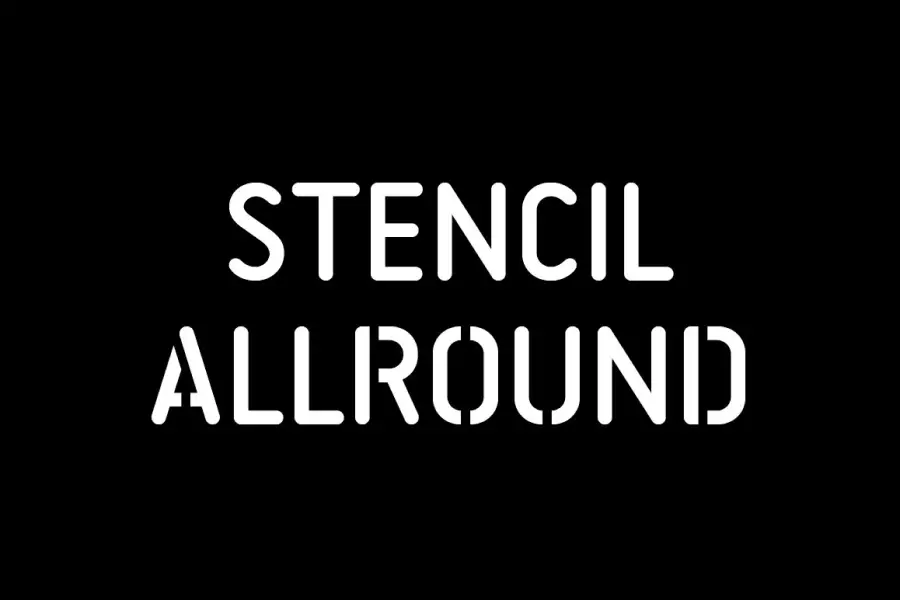
Stencil Allround는 둥근 대문자로 구성된 디스플레이 글꼴입니다. 이름에서 알 수 있듯이 스텐실 디자인이 특징이며 독특하고 눈길을 끄는 모양을 제공합니다. 포스터, 제목, 로고 등 다양한 디스플레이 프로젝트에 사용하기 위해 제작된 글꼴입니다.
Stencil Allround의 주요 기능 중 하나는 모서리가 둥글어서 부드럽고 접근하기 쉬운 모양을 제공합니다. 폰트도 가독성이 높아 본문이 큰 텍스트에 사용하기에 적합합니다. 또한 스텐실 디자인은 전통적인 글꼴과 차별화되는 추가 레이어를 제공합니다.
콰스
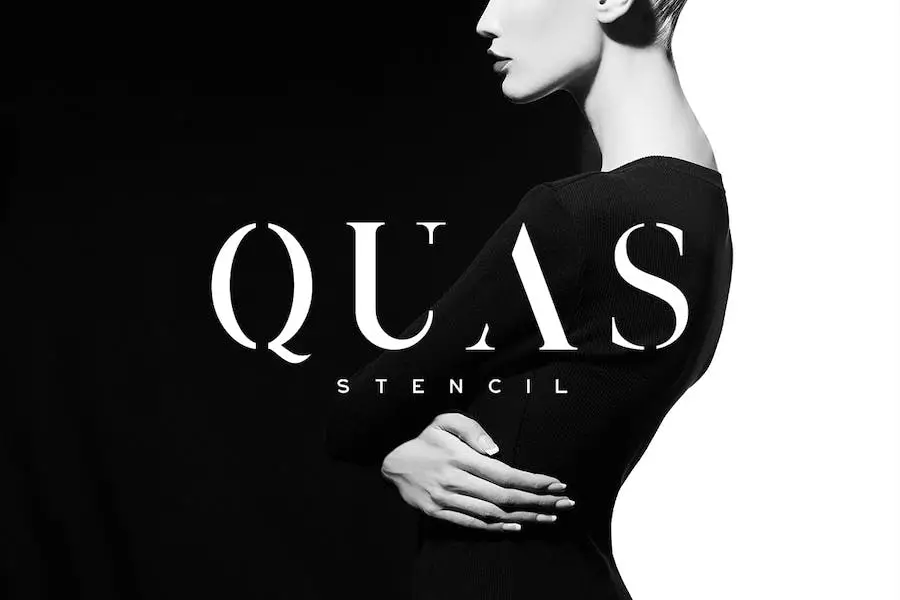
Quas는 그래픽 디자이너가 아름답고 세련된 헤드라인과 로고를 만드는 데 도움이 되는 탁월한 서체입니다. 스크립트 및 산세리프체와 완벽하게 작동하는 독특한 스타일을 가지고 있어 매우 다재다능합니다.
Quas의 가장 매력적인 기능 중 하나는 매끄럽고 우아한 디자인으로 브랜딩 프로젝트에 이상적입니다. 얇은 획과 부드러운 곡선은 어떤 디자인도 향상시킬 수 있는 현대적이고 세련된 외관을 제공합니다.
또한 Quas는 Regular, Bold 및 Italic을 포함하여 다양한 두께와 스타일로 제공되므로 디자이너가 원하는 효과를 얻기 위해 다양한 조합을 실험할 수 있습니다.
아미
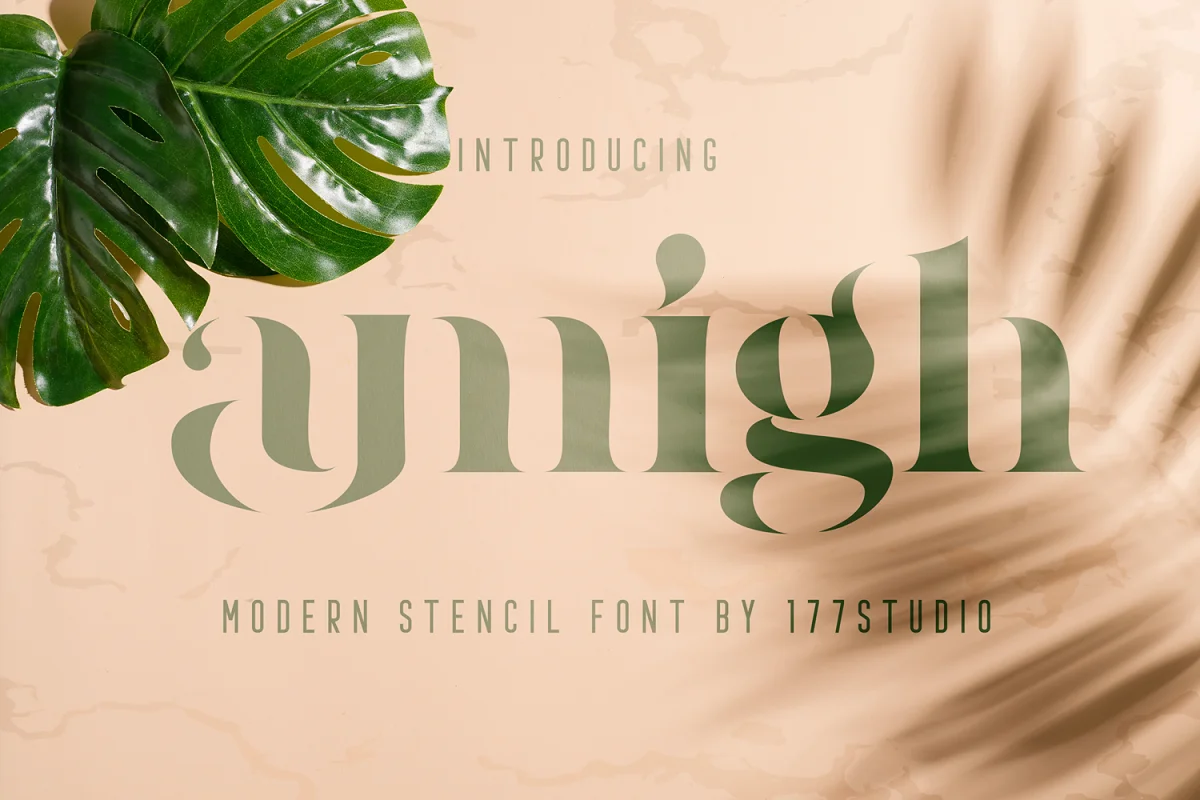
Amigh는 섬세함과 우아함을 발산하는 현대적이고 여성스러운 세리프 스텐실 글꼴입니다. 이 글꼴은 블로그, 패션, 예술 등과 같은 다양한 창의적인 프로젝트에 사용할 수 있습니다. 글씨체의 가독성은 최상급으로 작은 크기에서도 쉽게 읽을 수 있습니다.
글꼴에 포함된 합자는 고유성을 높이고 모든 대문자와 일부 소문자에 멋진 스타일을 더합니다.
글꼴에는 악센트 문자를 포함하여 대문자 및 소문자, 특수 합자, 스타일 대체, 숫자 및 구두점의 전체 세트가 함께 제공됩니다. 다양한 기능으로 모든 디자인 프로젝트에 다용도로 사용할 수 있으며 작업에 세련미와 우아함을 더해줍니다.
서른 아홉
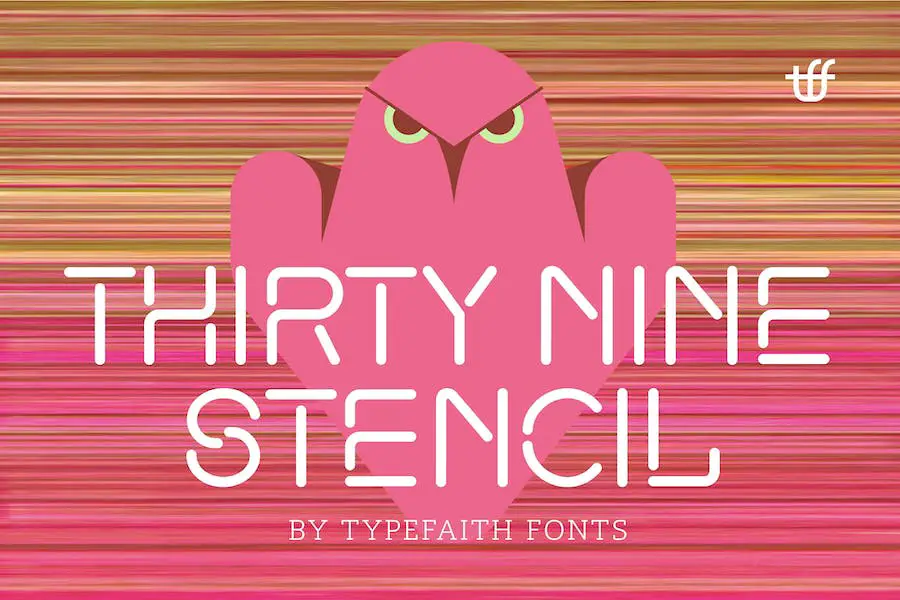
ThirtyNine은 디자인 프로젝트에 활력을 불어넣을 수 있는 창의적이고 독특한 스텐실 글꼴입니다. 종이나 레이저를 오려내거나, 네온 불빛을 만들거나, 나무에 새기는 데 이상적인 서체입니다.
세련되고 기하학적인 모양을 갖춘 ThirtyNine 스텐실은 로고, 워터마크, 앨범 표지, 브랜딩, 포스터, 전단지 및 책 표지에 강력한 메시지를 만들 수 있도록 도와줍니다.
이 글꼴은 뛰어난 다국어 지원을 제공하여 더 많은 사용자가 액세스할 수 있도록 합니다. ThirtyNine Stencil의 강하고 우아한 느낌은 오래된 디자인을 새롭고 신선한 것으로 바꿀 수도 있습니다.
브랜딩에 약간의 우위를 추가하거나 눈에 띄는 서명을 만들려는 경우 ThirtyNine Stencil이 지원합니다.
방바
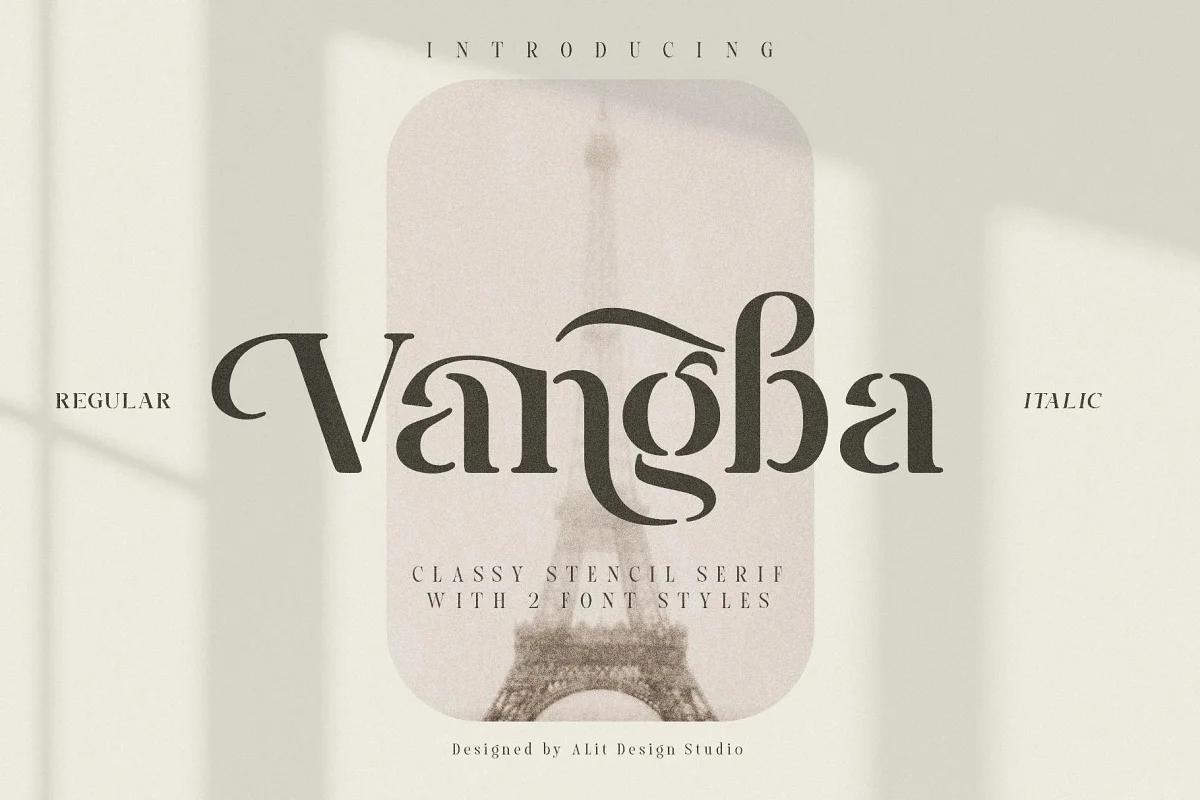
Vangba 글꼴은 모든 디자인에 우아하고 고전적인 느낌을 더하기에 완벽한 멋진 스텐실 스타일의 세리프 글꼴입니다. Vangba 글꼴은 불규칙하고 독특한 동적 모양을 가지고 있어 다른 글꼴과 차별화됩니다.
Vangba 글꼴 사용의 장점 중 하나는 다재다능함입니다. 레트로나 고급스러운 느낌이 나는 다양한 디자인에 활용 가능한 폰트입니다. 또한 사용자 친화적이며 유니코드(PUA)가 제공하는 지원으로 인해 디자인 및 비디자인 소프트웨어 프로그램 모두에서 잘 작동합니다.
점쟁이
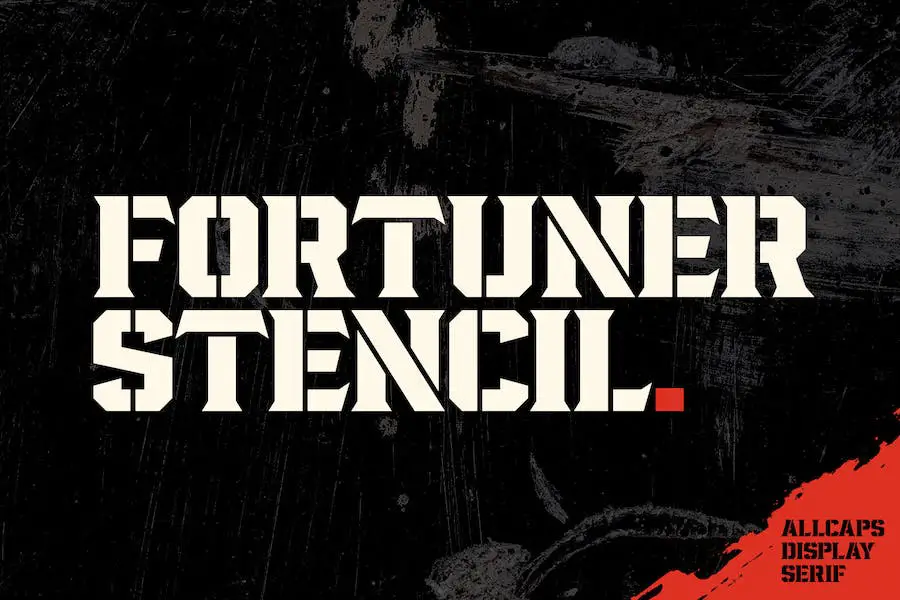
Fortuner는 디자인 프로젝트에 엣지 있는 느낌을 주는 글꼴입니다. 군사 또는 스포츠 테마로 스텐실 스타일의 서체가 있는 이 무거운 올캡 디스플레이 세리프는 대담한 표현을 원하는 사람들에게 적합합니다.
롤리
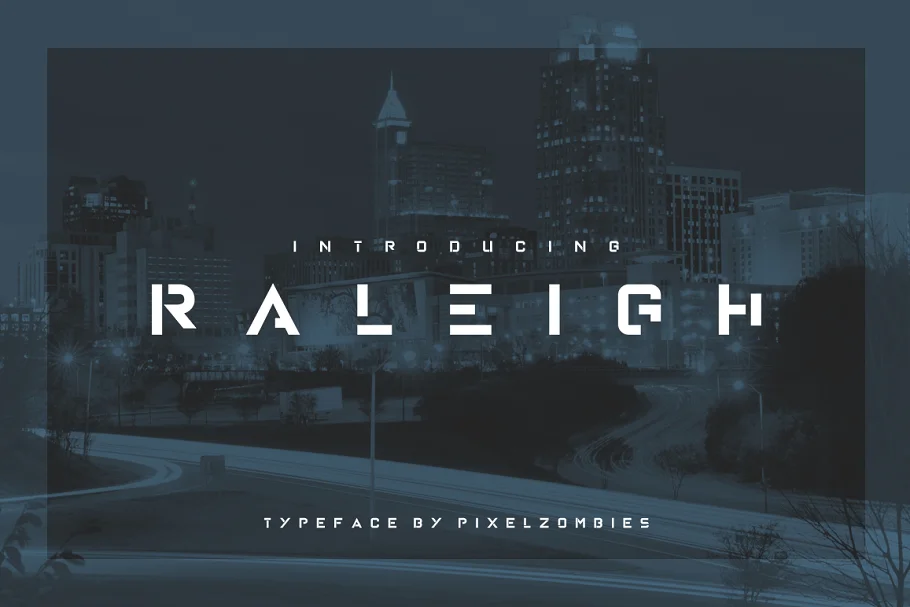
Raleigh는 미래적이면서도 현대적인 스텐실 같은 디자인으로 '서사시'를 발산하는 글꼴입니다. 프로젝트에 웅장함을 더하고 싶다면 이 글꼴이 적합할 것입니다.
Raleigh를 사용하면 오래 지속되는 인상을 남기는 매력적인 제목과 눈길을 끄는 하위 텍스트를 만들 수 있습니다. 글꼴의 고유한 스타일은 디자인에 흥미로운 요소를 추가하여 놓치기 어렵게 만듭니다.
펄론
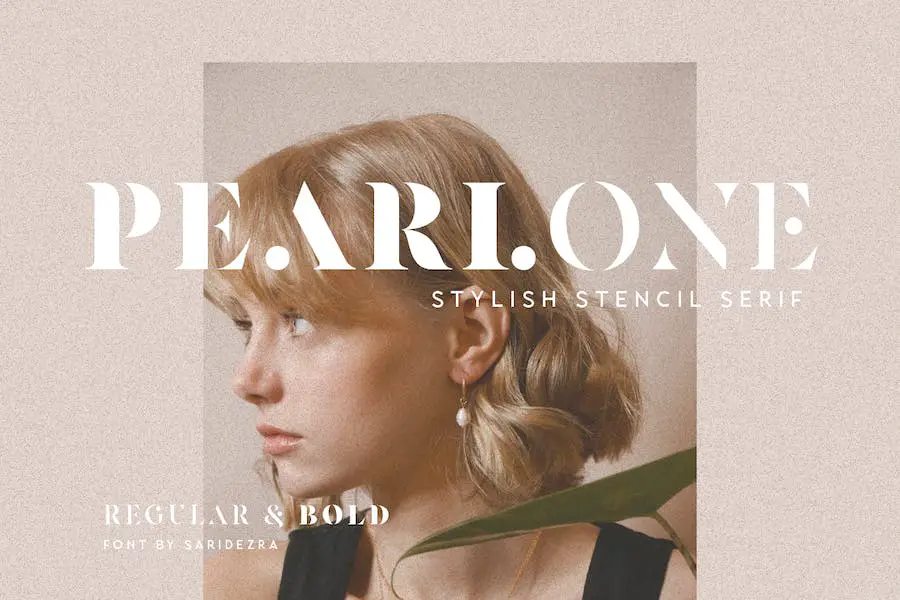
Pearlone은 현대적이고 스타일리시한 스텐실 세리프 글꼴로 디자인 프로젝트에 우아한 느낌을 더해줍니다. 진주의 아름다움에서 영감을 받은 이 글꼴은 일부 문자에 고유한 도트가 있어 매력과 세련미를 더합니다.
일반 스타일과 대담한 스타일로 제공되는 Pearlone은 시선을 사로잡는 놀라운 대비를 제공합니다. Pearlone의 좋은 점은 일반 형식 또는 특수 Pearl 버전과 함께 사용할 수 있는 옵션이 있다는 것입니다.
일반 형식에는 대문자를 사용하고 진주 버전에는 소문자를 사용하십시오. 이 다재다능한 글꼴은 브랜딩 로고에서 포스터, 편집 콘텐츠에 이르기까지 모든 용도로 사용할 수 있습니다. 또한 여러 언어를 지원하므로 글로벌 프로젝트에 사용할 수 있습니다.
아트렉 스텐실
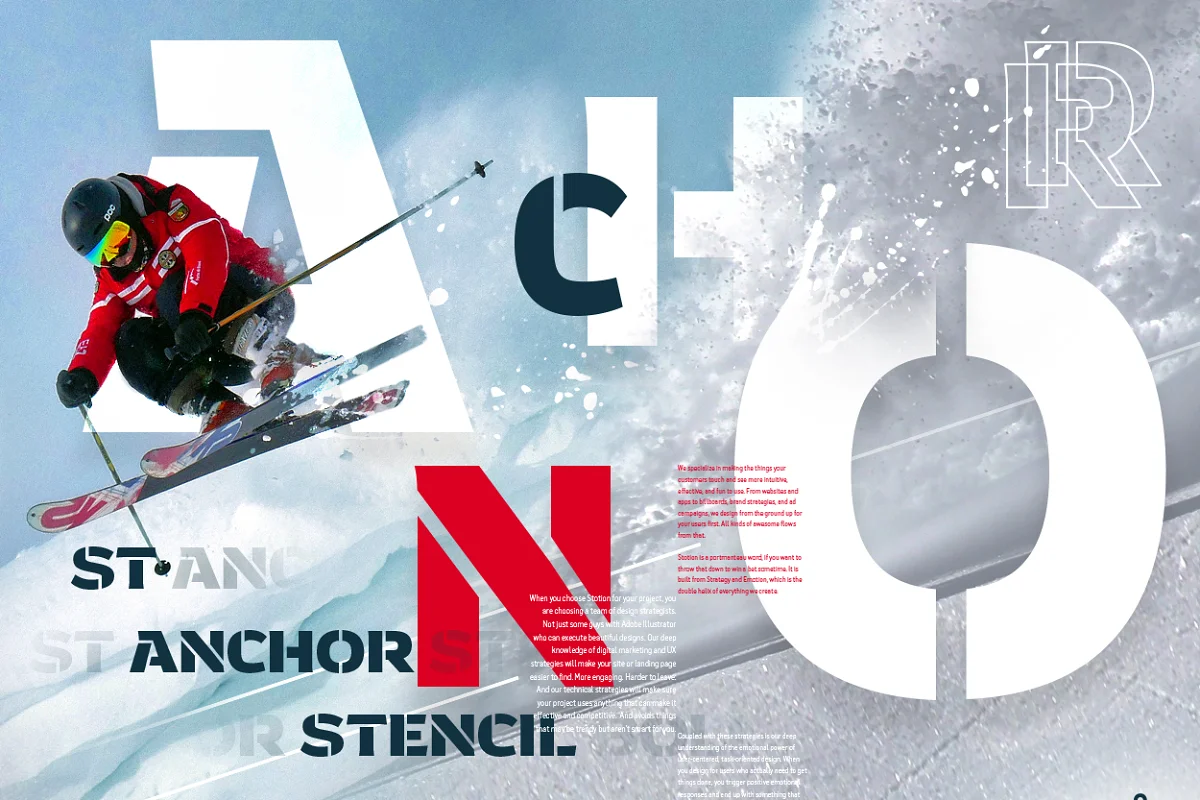
Atrek Stencil은 Atrek 글꼴 제품군에 새롭게 추가된 강력한 글꼴입니다. 이 스텐실 컷은 모든 프로젝트를 향상시킬 수 있는 대담하고 임팩트 있는 외관을 제공합니다. 아트렉 스텐실의 둥근 형태는 강렬했던 캐릭터에 부드러움을 더해 시선을 사로잡는 균형감을 만들어냅니다.
전반적으로 Atrek Stencil은 Word용 고품질 스텐실 글꼴을 찾는 사람들에게 훌륭한 옵션입니다. 강력한 컷, 둥근 형태, 가독성을 갖춘 이 글꼴은 모든 프로젝트에서 깊은 인상을 남길 것입니다.
쿠라인
Coutline은 다양한 창의적 프로젝트에 적합한 환상적인 전체 대문자 스텐실 디스플레이 글꼴입니다. 밀리터리 디자인과 도시 그래피티에서 영감을 받은 이 산세리프 글꼴은 모든 프로젝트를 향상시킬 수 있는 독특한 스타일을 자랑합니다.
Coutline을 돋보이게 만드는 것 중 하나는 다재다능함입니다. 로고, 브랜딩 자료, 소셜 미디어 게시물 또는 제품 포장을 만들 때 이 글꼴은 청중의 관심을 끌 수 있는 손글씨 맛을 전달합니다. 20개 이상의 다양한 언어 지원 옵션을 제공하므로 Adobe Illustrator, Photoshop, InDesign 및 Microsoft Word에서도 이 글꼴에 액세스할 수 있다는 것은 놀라운 일이 아닙니다.
루피나
Rufina는 심플함, 섬세함, 우아함을 담은 서체 패밀리입니다. 프로젝트를 향상시키기 위해 우아하면서도 미묘한 방법을 찾는 디자이너에게 적합합니다.
Rufina의 기본 개념은 밝은 배경의 조합에 어두운 텍스트를 사용하여 미묘하고 우아한 방식으로 보는 사람의 시선을 사로잡는 세련되고 먼 서체를 만들어 냈습니다.
Rufina를 독특하게 만드는 것은 서예가의 펜의 감동적인 터치와 Bodoni에서 영향을 받은 대조되는 형태의 조화입니다.
이 패밀리는 두 개의 가중치, 이탤릭체 대응물 및 대체 컷 세트로 구성되며 각 컷에는 다양한 삽화 장식이 포함되어 있습니다. 대안은 디자이너에게 다양한 디자인 옵션을 제공하여 다양한 유형의 프로젝트에 적합합니다.
달러 스텐실
Dollar Stencil은 모든 디자인 프로젝트에 우아함을 더할 수 있는 세련되고 세련된 글꼴입니다.
이 전체 대문자 글꼴은 지폐에서 영감을 받은 스텐실 세리프 디자인을 자랑하며 클래식하고 빈티지한 느낌을 줍니다. 레트로 또는 구식 분위기의 디자인을 만들고자 하는 모든 사람에게 적합합니다.
Dollar Stencil의 두드러진 특징 중 하나는 다양성입니다. 포스터, 로고 또는 웹사이트 헤더를 디자인하든 이 글꼴은 다양한 설정에서 사용할 수 있습니다.
대담하고 눈길을 끄는 외관은 제목과 헤드라인에 이상적이며 깔끔한 선은 더 작은 크기에서도 가독성을 유지합니다.
피구라티카
Figuratika는 짧은 텍스트, 제목, 로고, 포스터 등에 완벽하게 어울리는 세련되고 스타일리시한 아르데코 스텐실 글꼴입니다. 레트로한 느낌의 대담한 디자인이 돋보이는 기하학적인 서체입니다.
프로젝트에 빈티지한 매력을 더해주는 스텐실 글꼴을 찾고 있다면 Figuratika를 고려해 볼 가치가 있습니다. 기하학적인 아르데코 스타일과 대담한 디자인은 텍스트를 돋보이게 만들고 보는 사람의 시선을 사로잡을 것입니다.